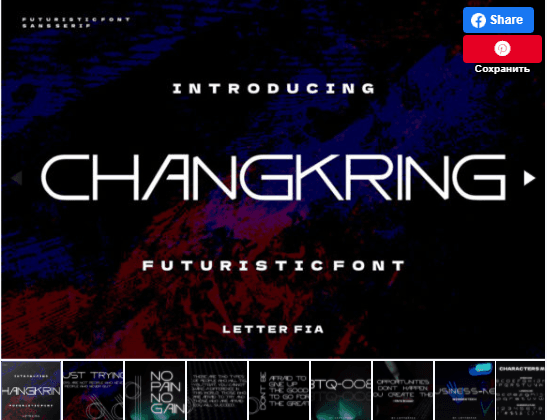
Changkring Font
Changkring - футуристический и минималистичный дисплейный шрифт. Этот шрифт идеально подходит для написания веб-дизайнов, визиток и всего остального, что требует уникального подхода.